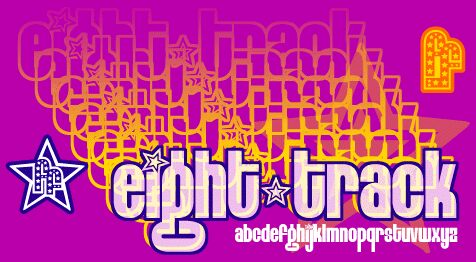
Eight Track Program 3 von Font"a"licious Fonts ist eine kostenlose, groovige Display-Schrift mit fetten, blasenartigen Buchstaben und einer markanten, dicken Outline. Die Formen erinnern an Retro-Cartoons: hochkant, aufrecht, mit weichen Ecken und einem verspielten Stern-Detail, das wie ein Sticker hervorsticht. Die hohlen Innenflächen laden dazu ein, mit Farben, Verläufen oder Texturen zu spielen, und sorgen im Handumdrehen für einen mehrschichtigen Look ohne großen Aufwand.
Mit Eight Track Program 3 fallen deine Headlines sofort ins Auge – perfekt für Party-Flyer, Kinderbücher, Retro-Game-Titel, Merchandise, Social-Media-Posts und auffälliges Branding. Diese kostenlose Schrift glänzt besonders, wenn du ihren lauten, konturierten Stil voll auskostest und sie für den nötigen Kontrast mit einer schlichten serifenlosen Schrift kombinierst. Probiere aus, kurze Wörter zu stapeln, den Zeilenabstand zu verringern und die Innenflächen mit knalligen Farben zu füllen, um den vollen Groove-Vibe zu erzielen.